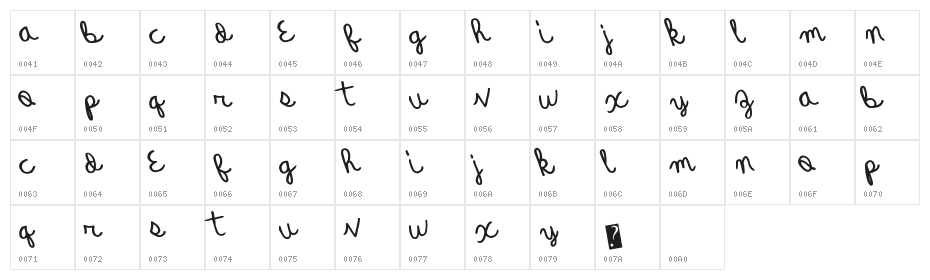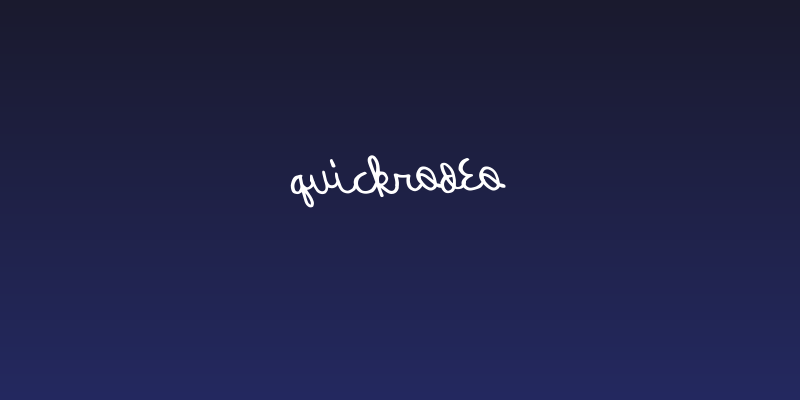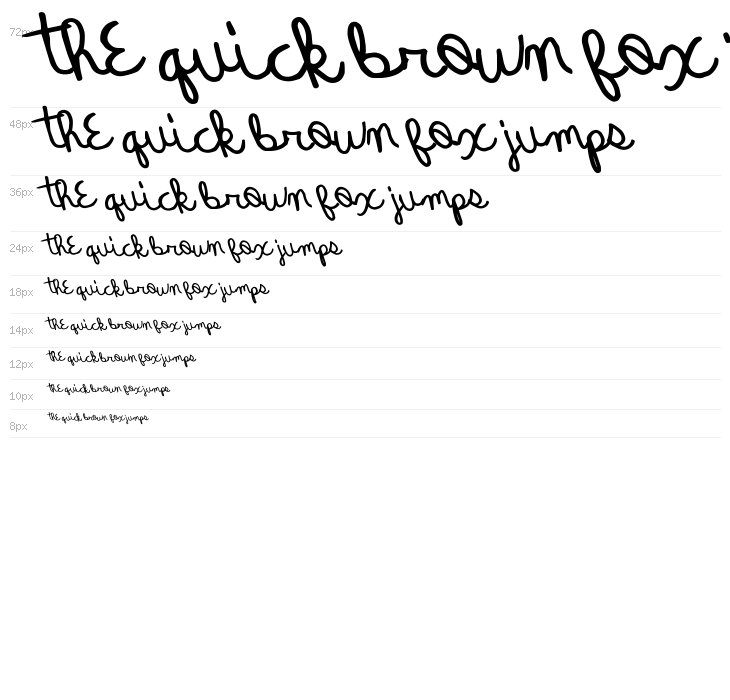
QuickRodeo Font
| Stile generale | Casual and Creative |
| Caso d'uso | Headlines, Invitations, Personal Branding |
| Progetti proposti | Ideal for greeting cards, invitations, personal branding, and creative projects that require a personal touch. |